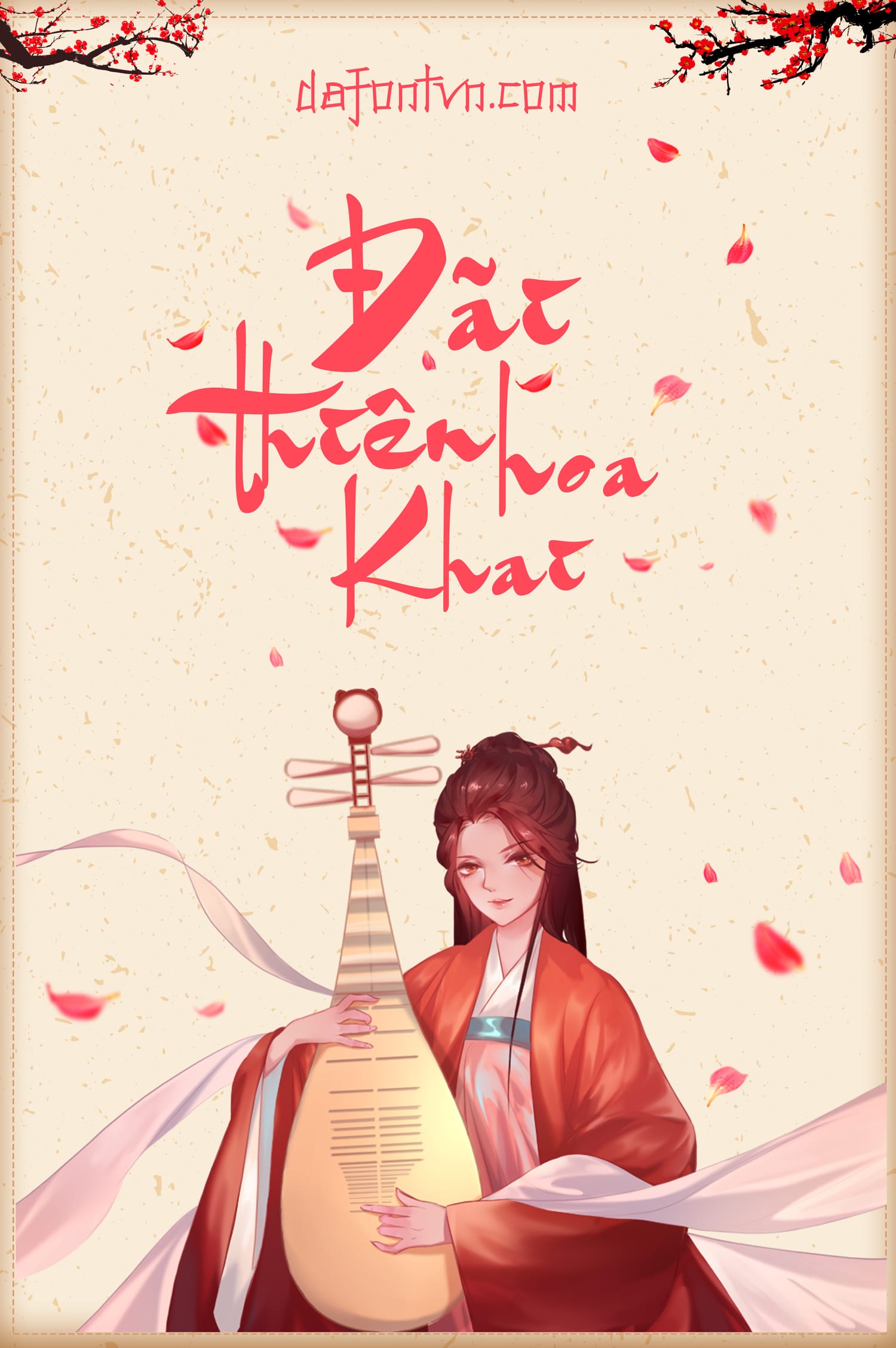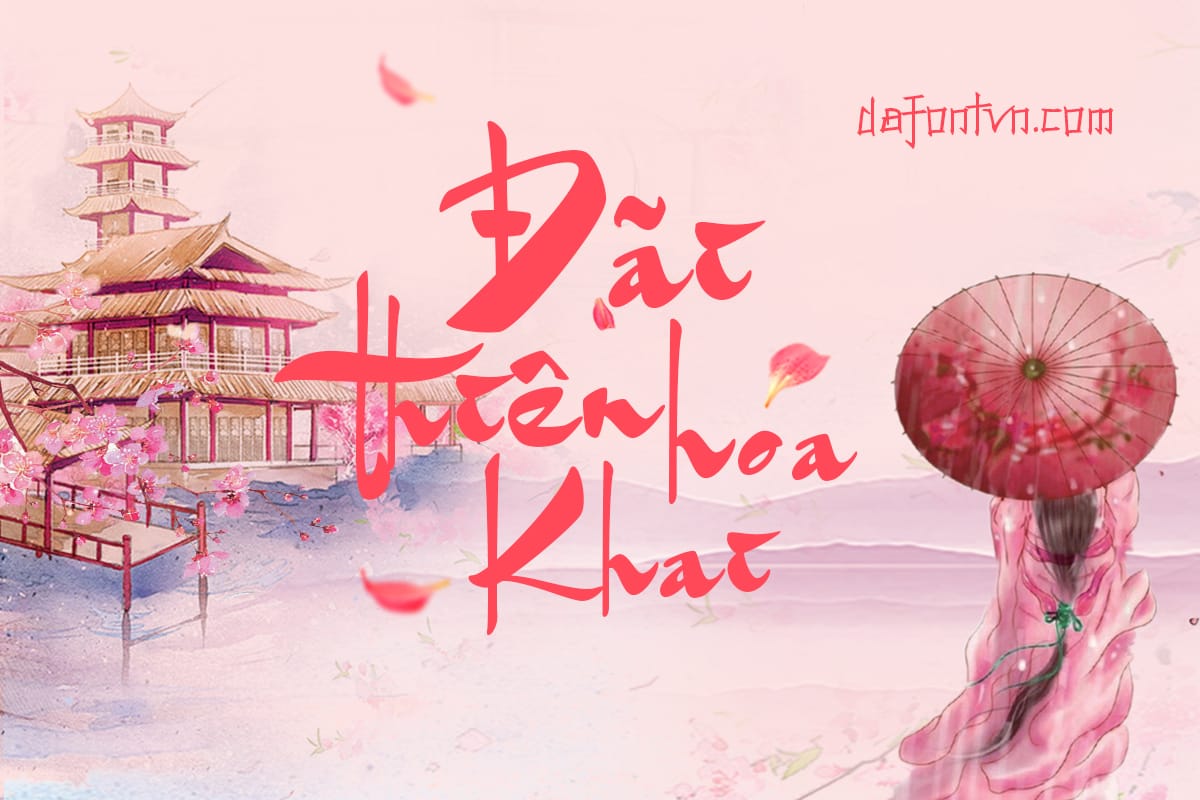
Goatskin Brush Font là một kiểu font mang phong cách thư pháp rất phù hợp cho các thiết kế cổ trang, bìa truyện, typo hoặc bất kỳ thiết kế nào khác. Font Goatskin Brush việt hóa đầy đủ, thêm các ký tự số và chỉnh sửa lại một chút so với font gốc.